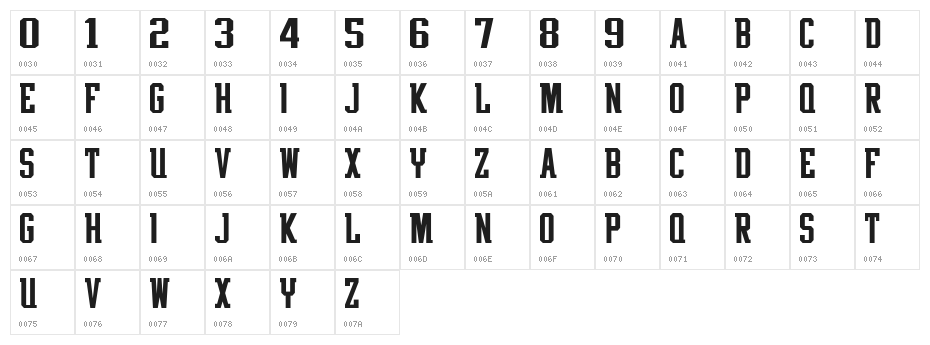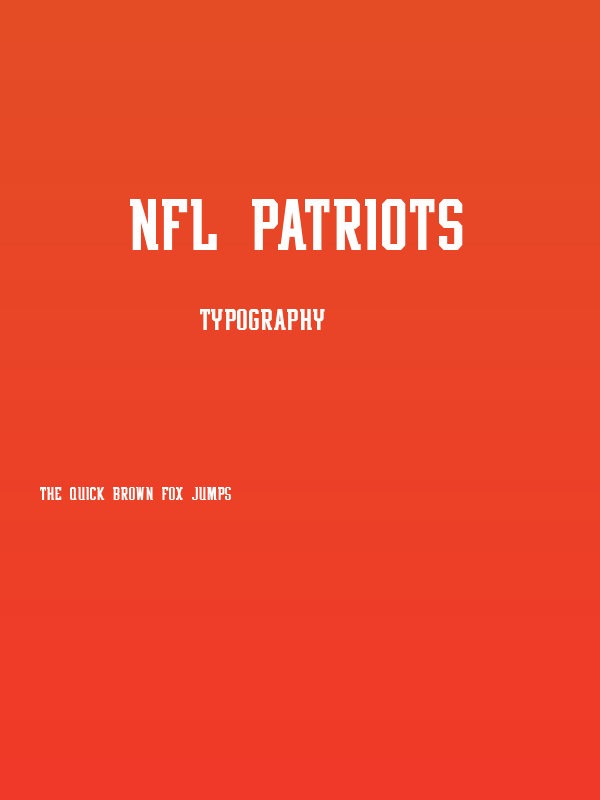
NFL Patriots Font
| Caso de uso | Logos, Headlines, Sports Branding |
| Proyectos propuestos | Ideal for sports branding, team logos, merchandise, posters, and headlines that require a bold and assertive look. |